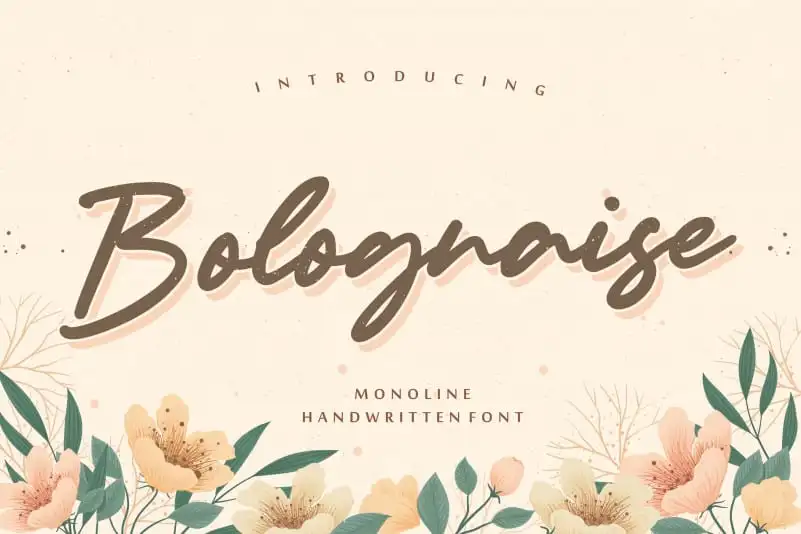
Bolognaise Monoline Handwritten Font – Download Grátis
A Bolognaise Monoline Handwritten Font é uma escolha perfeita para aqueles que buscam personalidade e elegância em suas produções digitais. Especialmente indicada para aplicativos de marca, embalagens de produtos, revistas, mídias sociais, casamentos ou simplesmente qualquer texto de destaque sobre fundo neutro, ela captura a essência dos elementos que deseja destacar com elegância e originalidade. Seu estilo monolineado oferece uma simplicidade única que se adapta perfeitamente à natureza moderna das redes sociais e do design gráfico atual. Ao mesmo tempo, a sua escrita frondosa e natural transmite um toque de personalização perfeito para ambientes mais formais, como embalagens ou revistas de alto padrão. Esta fonte é uma ótima opção para quem busca uma maneira única de expressar o seu negócio através do design visual. Seja no papel ou na tela, ela certamente impressionará seus seguidores e consumidores com sua presença assertiva.